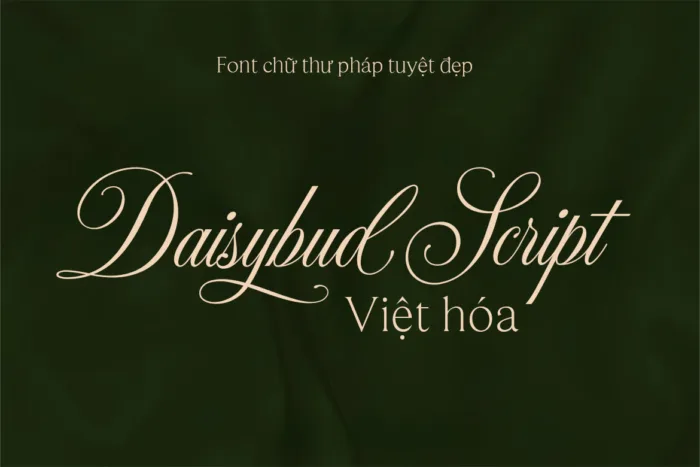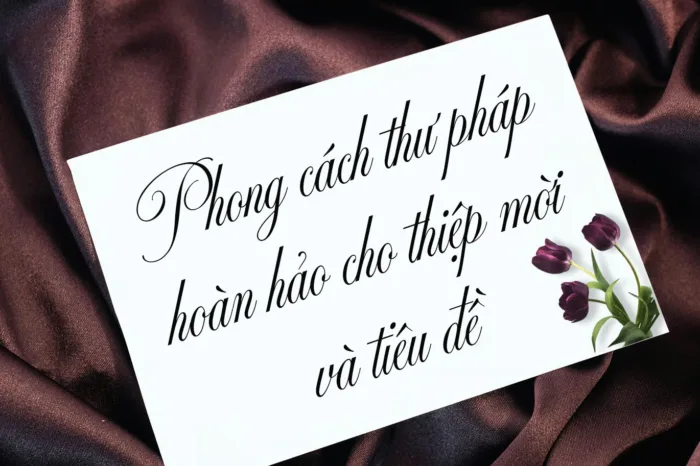
DVN Daisybud Script Việt hóa – Font chữ thư pháp tuyệt đẹp phiên bản sữa lỗi dấu và đủ bộ số
DVN Daisybud Script Việt hóa là một font chữ thư pháp tuyệt đẹp, mang phong cách mềm mại và bay bướm, lý tưởng cho các thiết kế thiệp, lời chúc, poster nghệ thuật và các dự án sáng tạo khác. Phiên bản Việt hóa này đã được chăm chút kỹ lưỡng với việc sửa lỗi dấu tiếng Việt và bổ sung đầy đủ bộ ký tự số, giúp font hoạt động hoàn hảo trong mọi tình huống sử dụng. Những đường nét uyển chuyển, thanh thoát của DVN Daisybud Script tạo cảm giác tinh tế và lãng mạn, rất phù hợp cho các thiết kế mang hơi hướng nữ tính hoặc hoài cổ. Font hỗ trợ đầy đủ bảng chữ cái tiếng Việt có dấu, mang lại trải nghiệm mượt mà và nhất quán trong từng dòng chữ. Nếu bạn đang tìm một font script vừa đẹp mắt vừa tiện dụng cho thiết kế tiếng Việt, DVN Daisybud Script Việt hóa chắc chắn là lựa chọn không nên bỏ qua.